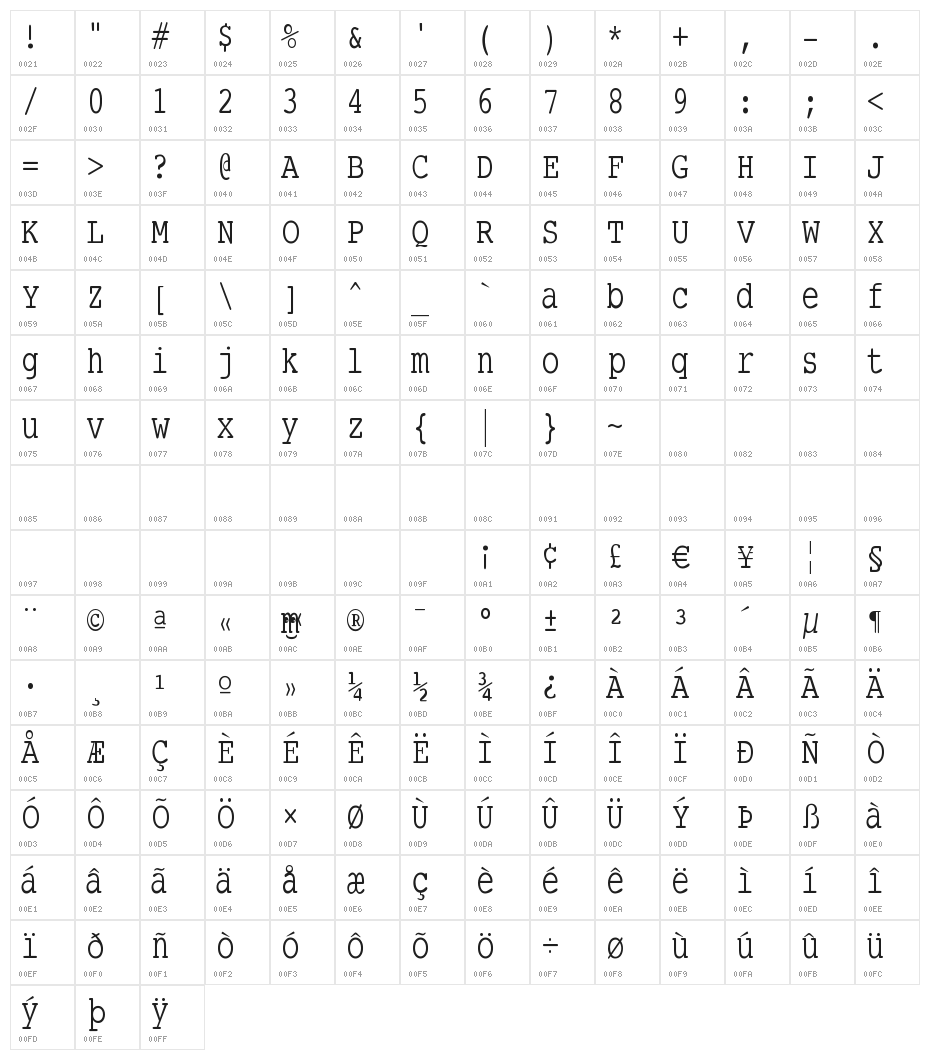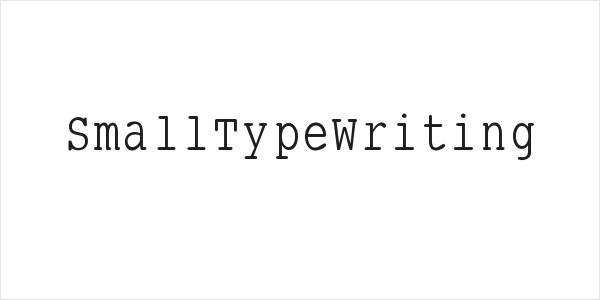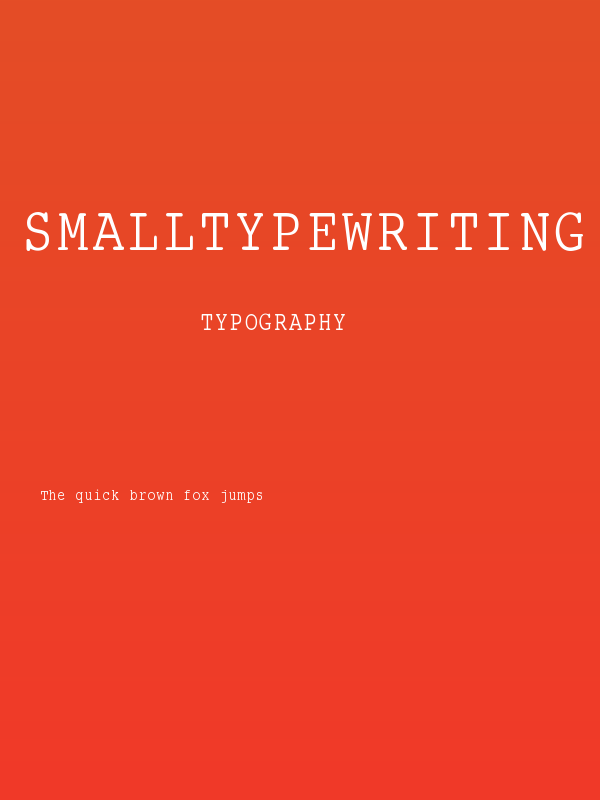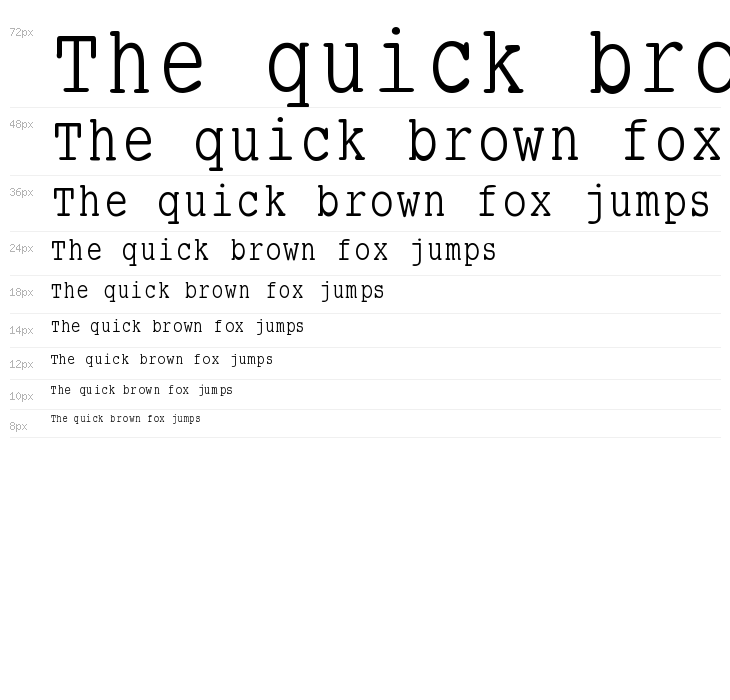
SmallTypeWriting Font
| Categorie | Typewriter |
| Spaziatura caratteri | Normal |
| Caso d'uso | Headlines, Body text, Logos, Coding |
| Progetti proposti | Ideal for creating retro-themed designs, typewriter-style documents, coding environments, and any project requiring a vintage aesthetic. |
| È fissato Pitch | Yes |